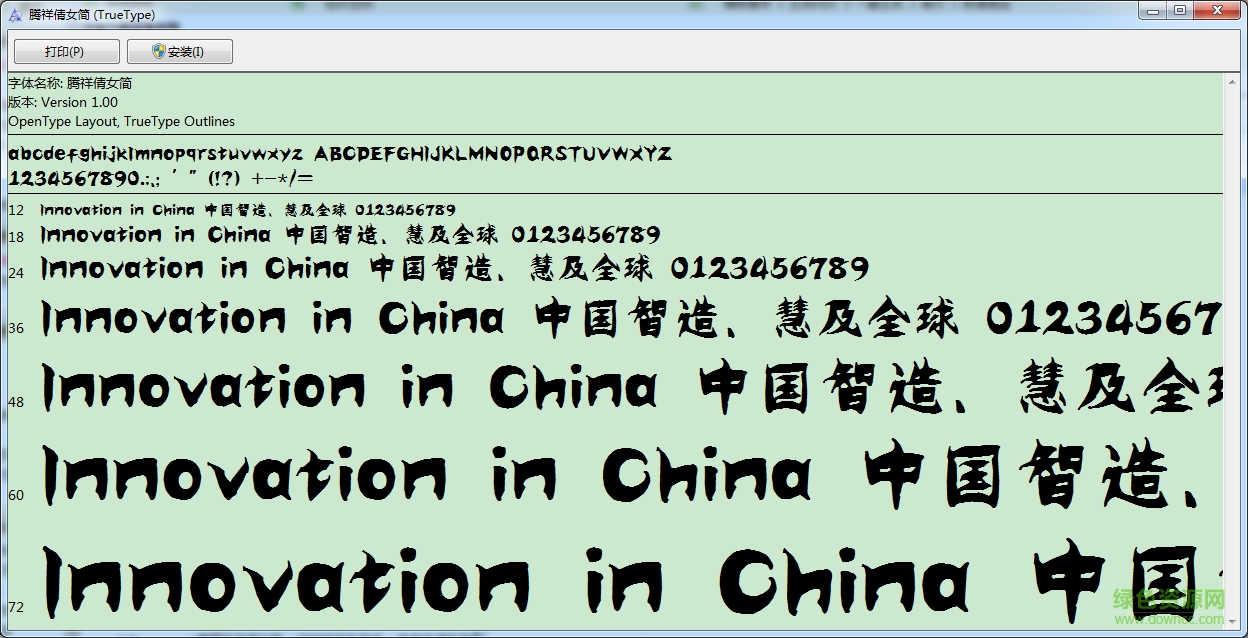
騰祥倩女簡是一款獨具特色的藝術(shù)字體,這款字體字形清新秀逸,姿態(tài)婀娜似少女亭亭玉的倩女,字形十分有范,喜歡的朋友歡迎來綠色資源網(wǎng)下載使用!
騰祥倩女簡體,美術(shù)字體,此款字突出的靚點是將書法體與美術(shù)體巧妙結(jié)合渾然天成。利用行書的筆法,筆畫瀟灑流落,翰逸神飛,重筆觸大膽用墨,輕筆觸干凈利落,偏旁與字身勾連貫通自如流暢,又融入美術(shù)字的書寫特征很好地控制張力,保證每個字的風格統(tǒng)一、粗細得當、易于閱讀。然筆墨自然流動間又結(jié)構(gòu)端莊。